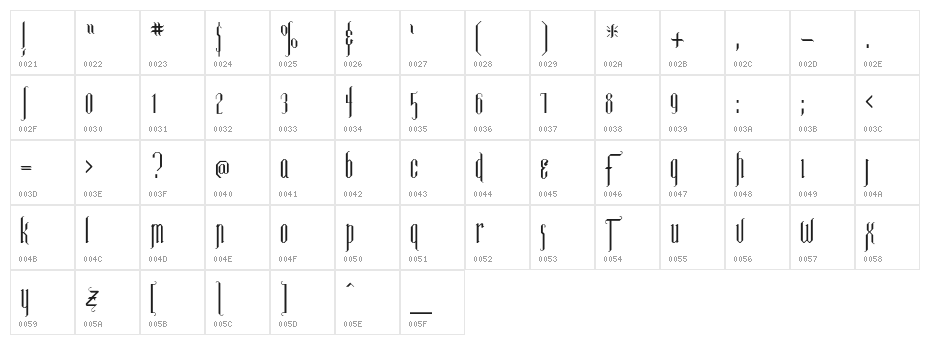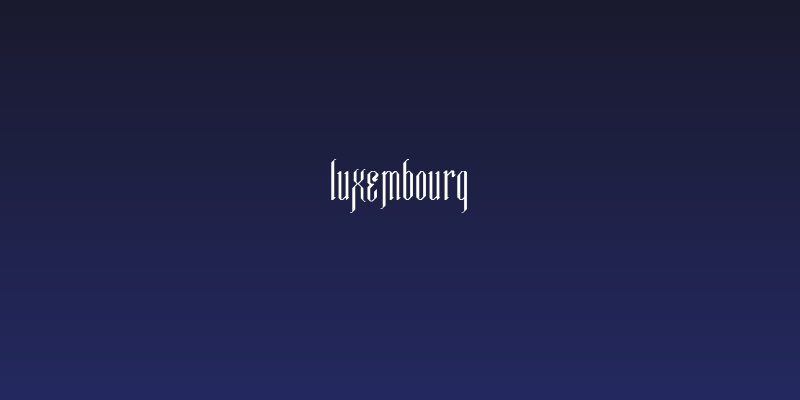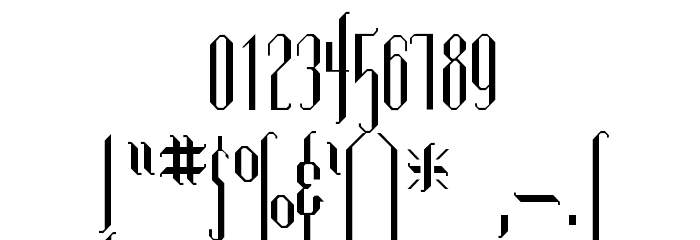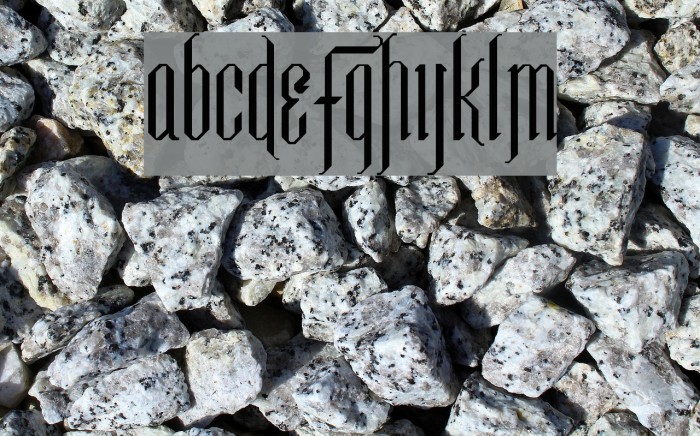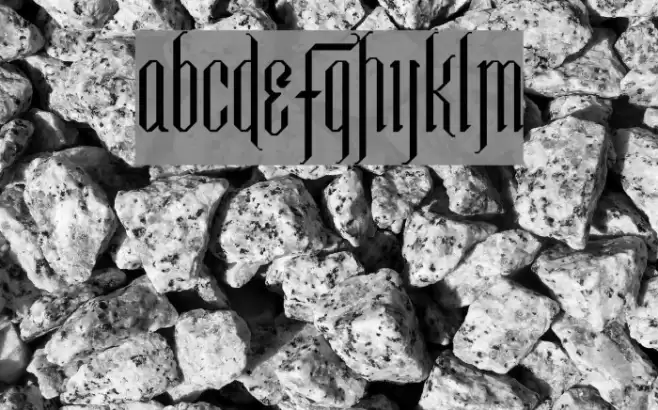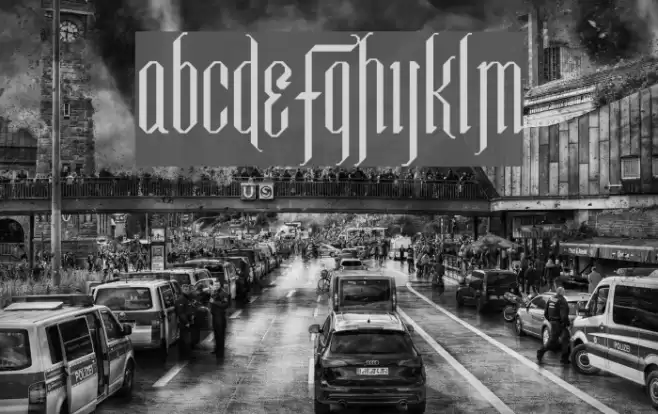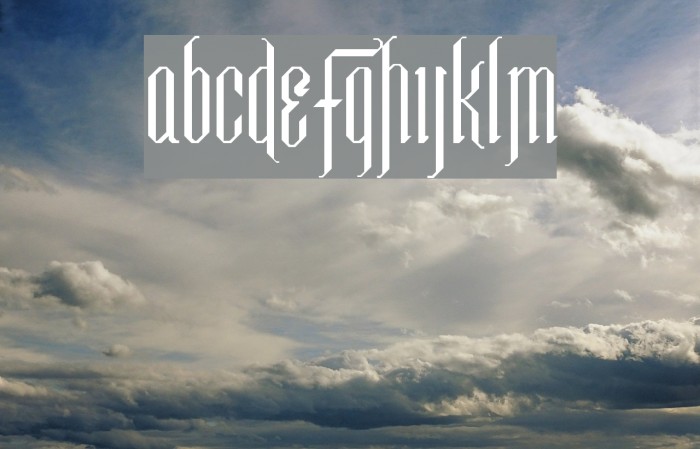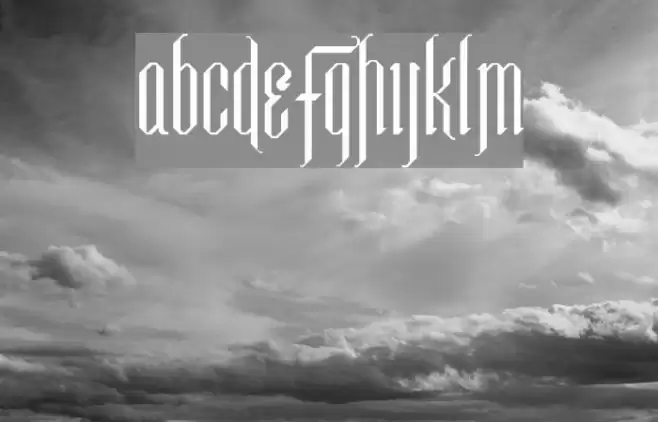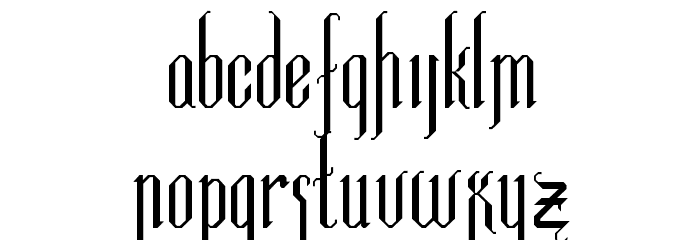
Luxembourg Font
| Cas d'utilisation | Headlines, Logos, Decorative text |
| Projets proposés | Suitable for historical documents, certificates, invitations, and branding that requires a classic and formal touch. |